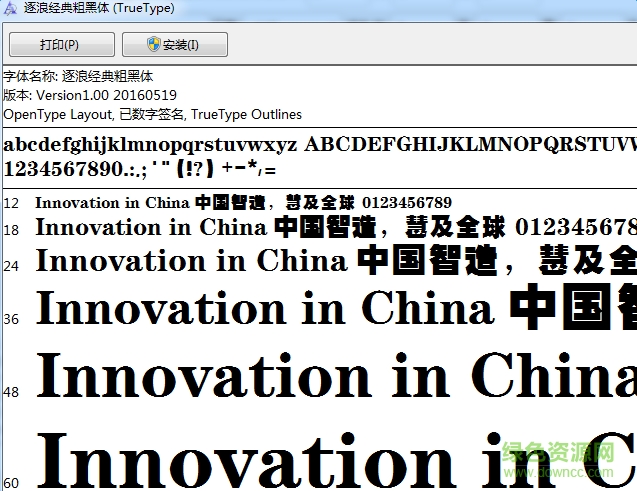
zoomlacuheia003字體
zoomlacuheia003字體是一款結(jié)構(gòu)方正飽滿的黑體字體,筆畫簡潔有力,線條粗壯雄峻,穩(wěn)重得體,非常醒目,常常用于標(biāo)題,有需要者歡迎免費(fèi)下載!
美術(shù)黑體字體介紹
1.清末民國期間大量出現(xiàn)的美術(shù)黑體與傳統(tǒng)裝飾文字之間的區(qū)別是明顯的。美術(shù)黑體幾何的筆型、機(jī)械的直線、透視的空間和模擬光照而形成的立體投影,這些細(xì)節(jié)處處流露出強(qiáng)烈的現(xiàn)代趣味與西方文明的痕跡;
2.而傳統(tǒng)裝飾文字則多以書法為審美參照,多表現(xiàn)自然物象。從裝飾元素來看,美術(shù)黑體多用三角形、方形、圓形等抽象形,或維多利亞風(fēng)格和新藝術(shù)風(fēng)格的相對抽象的植物元素;而裝飾文字中使用的各種自然形則少有抽象化的處理。
zoomlacuheia003字體